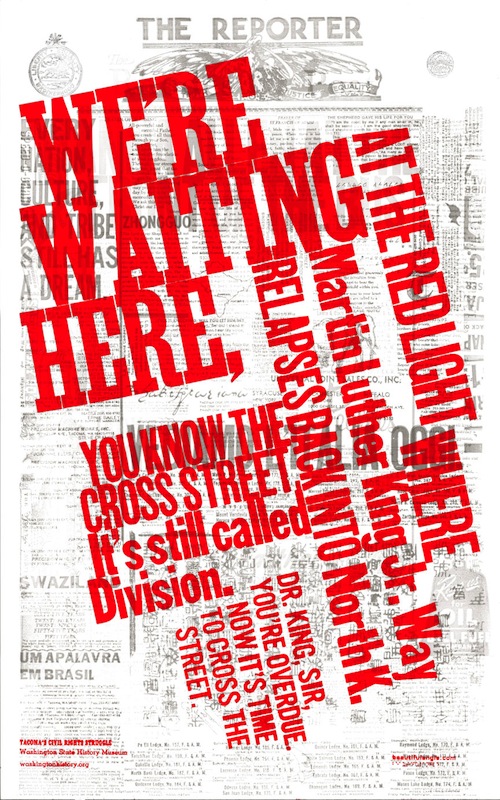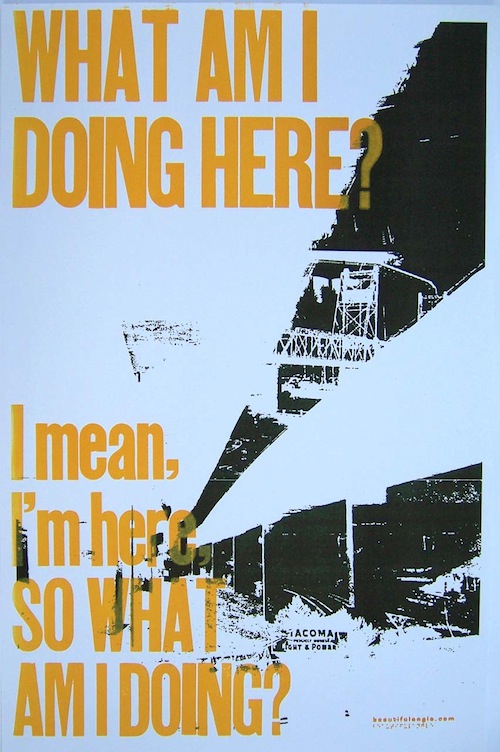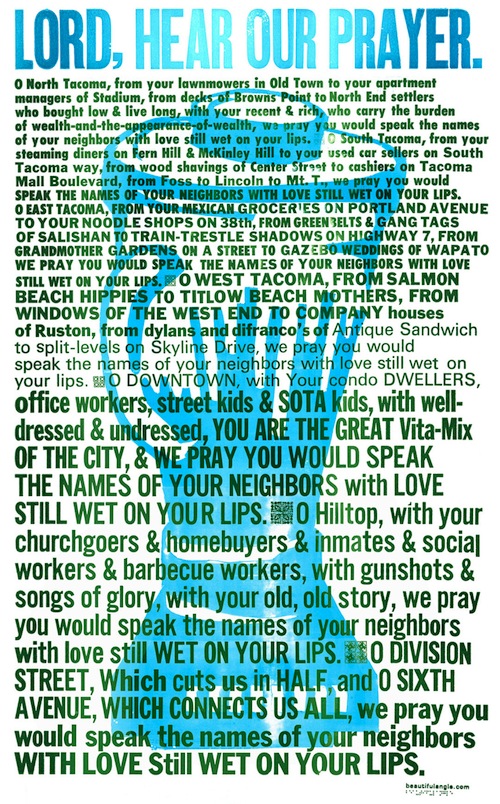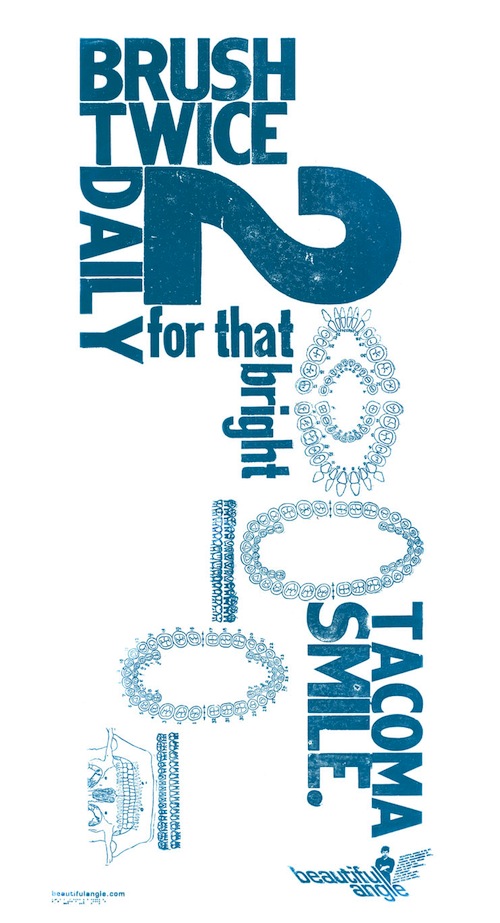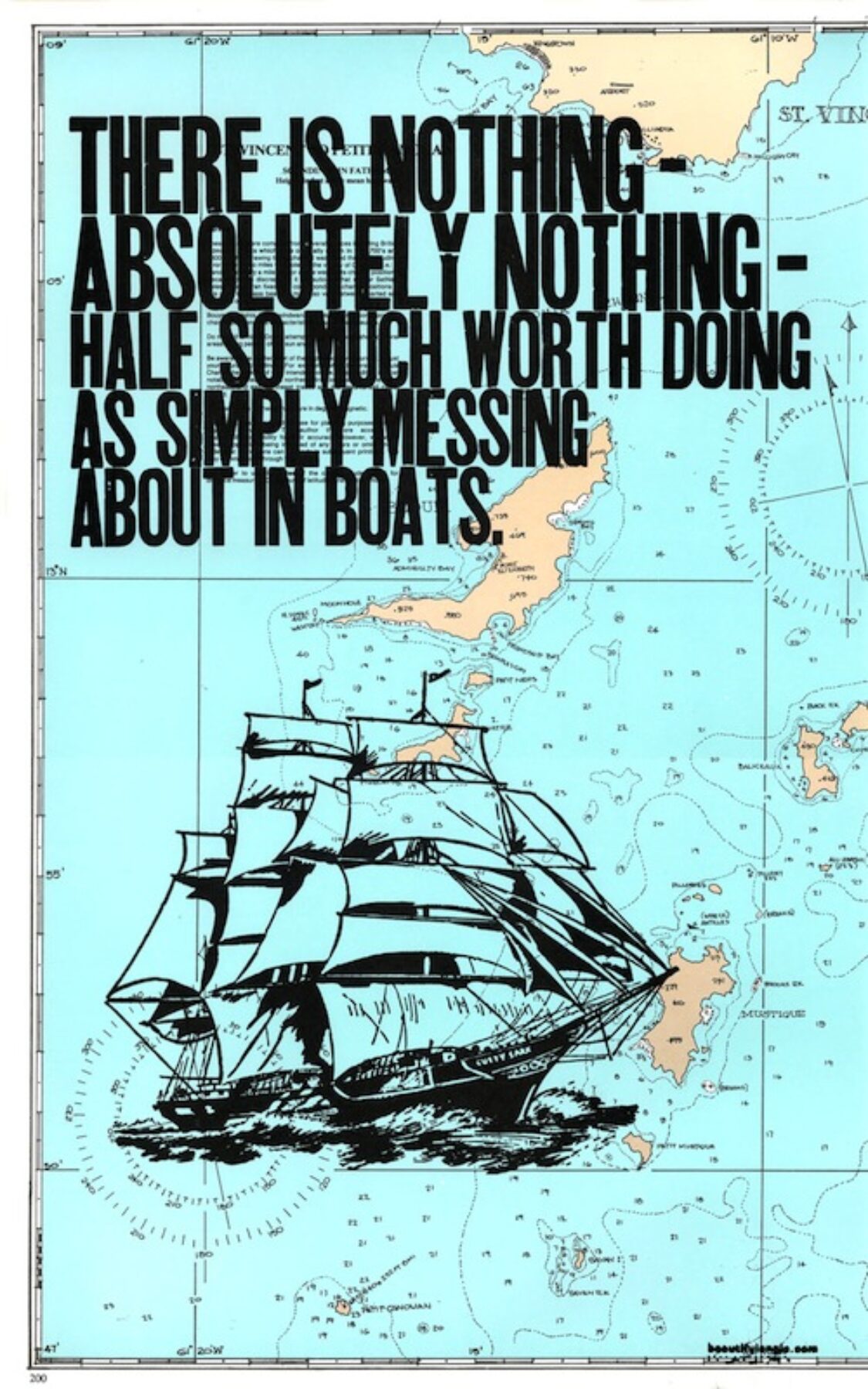
Poster tipográficos experimentais, é isso que você vai ver no portfólio do Beautiful Angle.beautifulangle.homestead.compreviousMegan CullennextHIV Related Posts Nos bastidores da nova tipografia personalizada de Wallace & Gromit por Jamie Clarke Buchstabenmuseum em Berlim: O fechamento do único museu de letras da capital alemã Swiss Cheese Mono: A Fonte Cheia de Caráter Leave a ReplyYour email address will not be published. Required fields are marked *Name * Email * Website Comment * Δ This site uses Akismet to reduce spam. Learn how your comment data is processed.Tags:ArteDesign GráficoportfolioTipografia